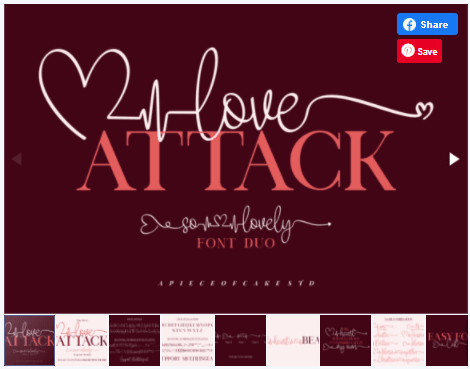
Love Attack Font
Love Attack - стильный и нежный рукописный дуэтный шрифт, подходящий для широкого спектра приложений. От поздравительных открыток до заголовков - вы можете добавить этот эффектный шрифт в любой из ваших творческих проектов, и он гарантирует им романтический рукописный вид.